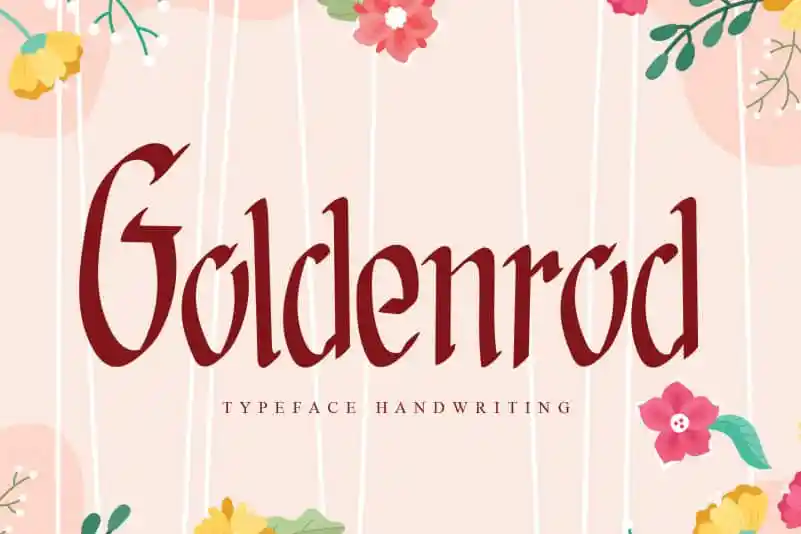
Goldenrod Script Font
A Goldenrod Script Font é uma elegante fonte escrita à mão que se destaca por sua fluidez e graça natural. Ideal para adicionar um toque especial a diversos tipos de projetos, como banners de parede, convites de casamento, logotipos em mídias sociais, anúncios, embalagens de produtos, designs de produtos, rótulos, fotografias e até mesmo marcas. A Goldenrod Script é perfeita para qualquer projeto que exija uma toque de escrita à mão única e personalizado. Sua versatilidade a torna uma escolha óbvia entre as fontes escritas à mão disponíveis no mercado, seja você um designer gráfico profissional ou iniciante.